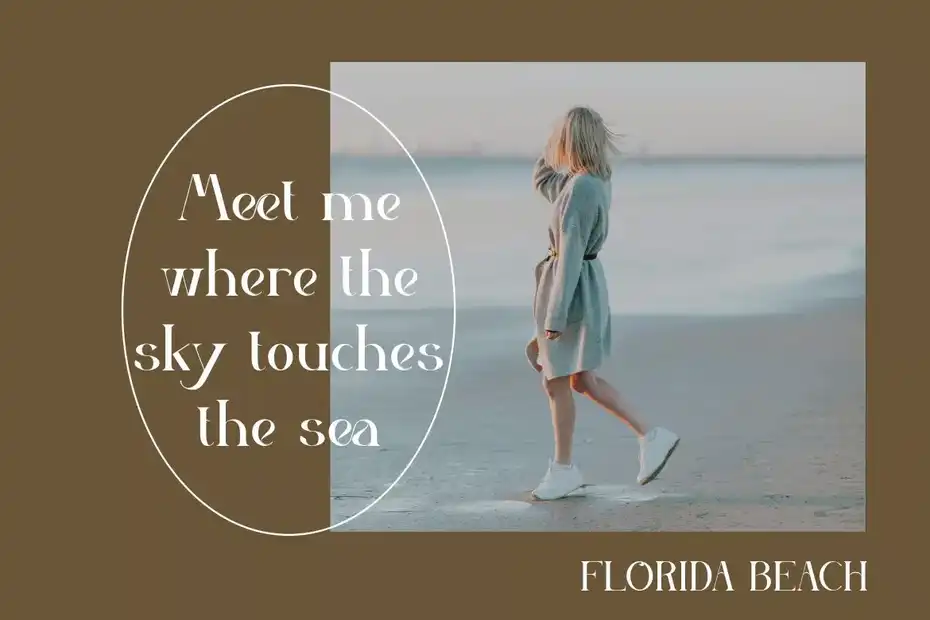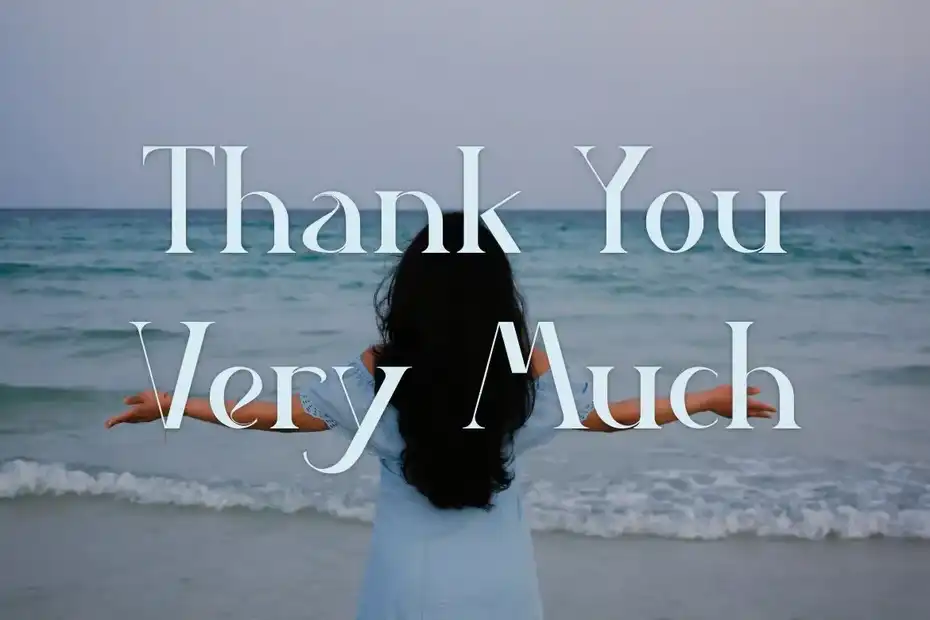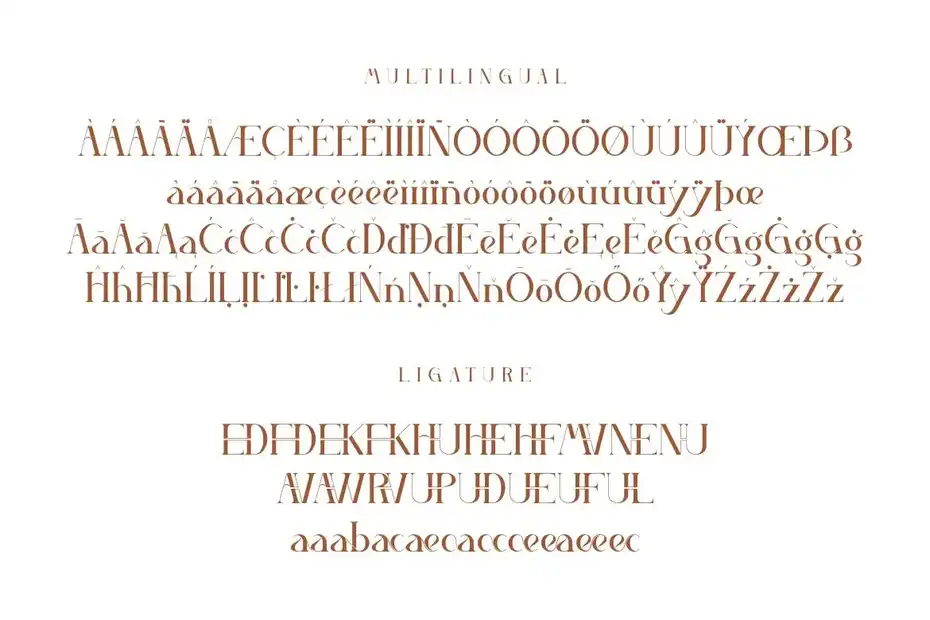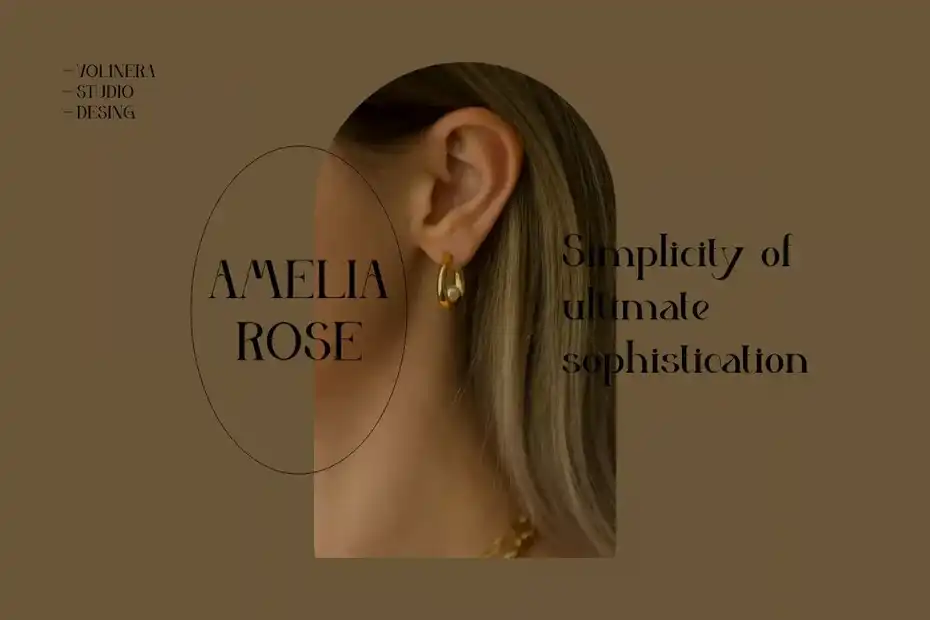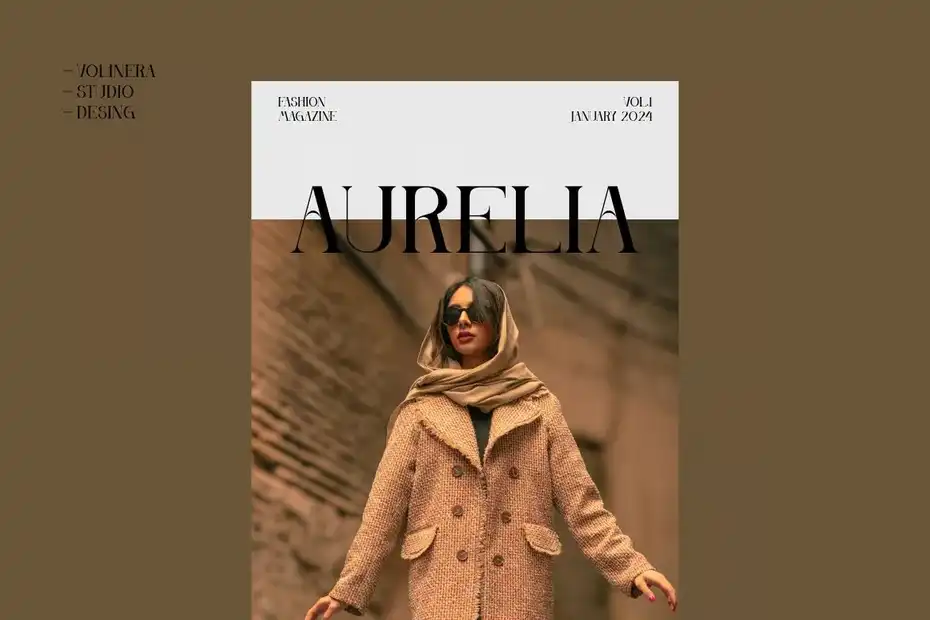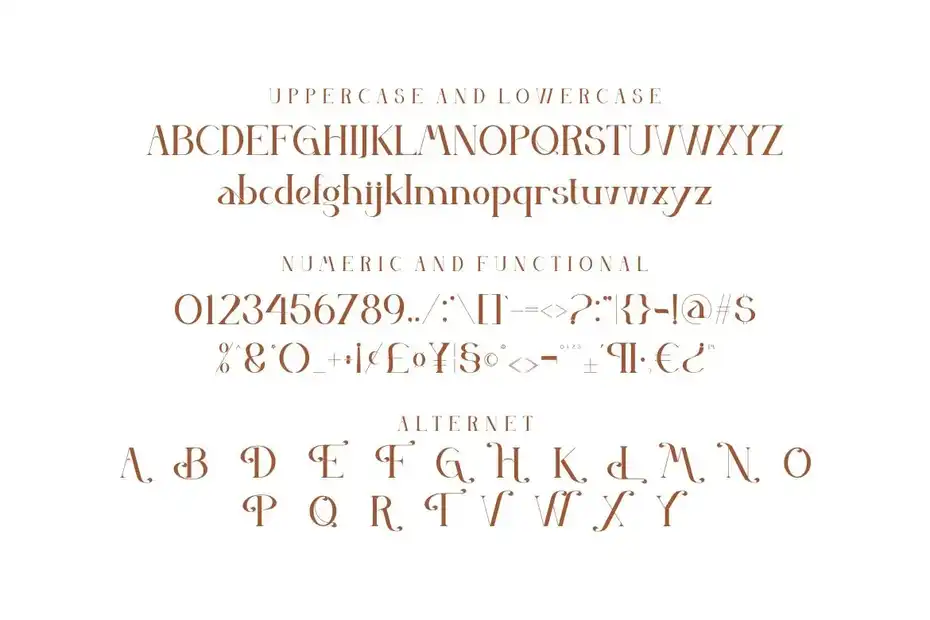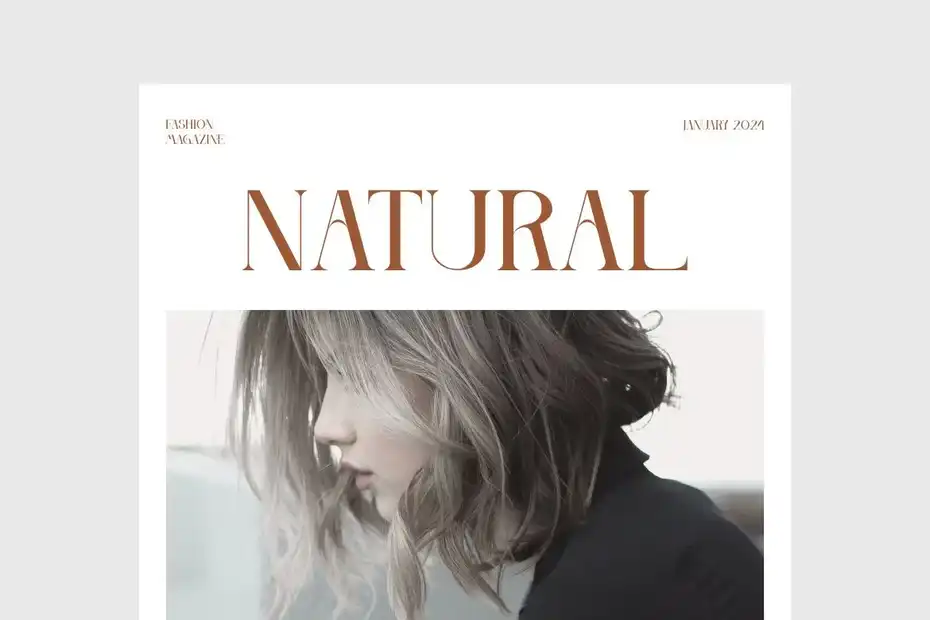
دانلود فونت Volinera Font
دانلود فونت Volinera Font : این مطلب شامل یک فونت انگلیسی مدرن است که برای لوگو، برندینگ محصول، نقل قول، سربرگ وبلاگ، پوستر، نامه، دعوت نامه و غیره مناسب میباشد.
• عنوان مجموعه: Volinera Font
• سبک: Serif